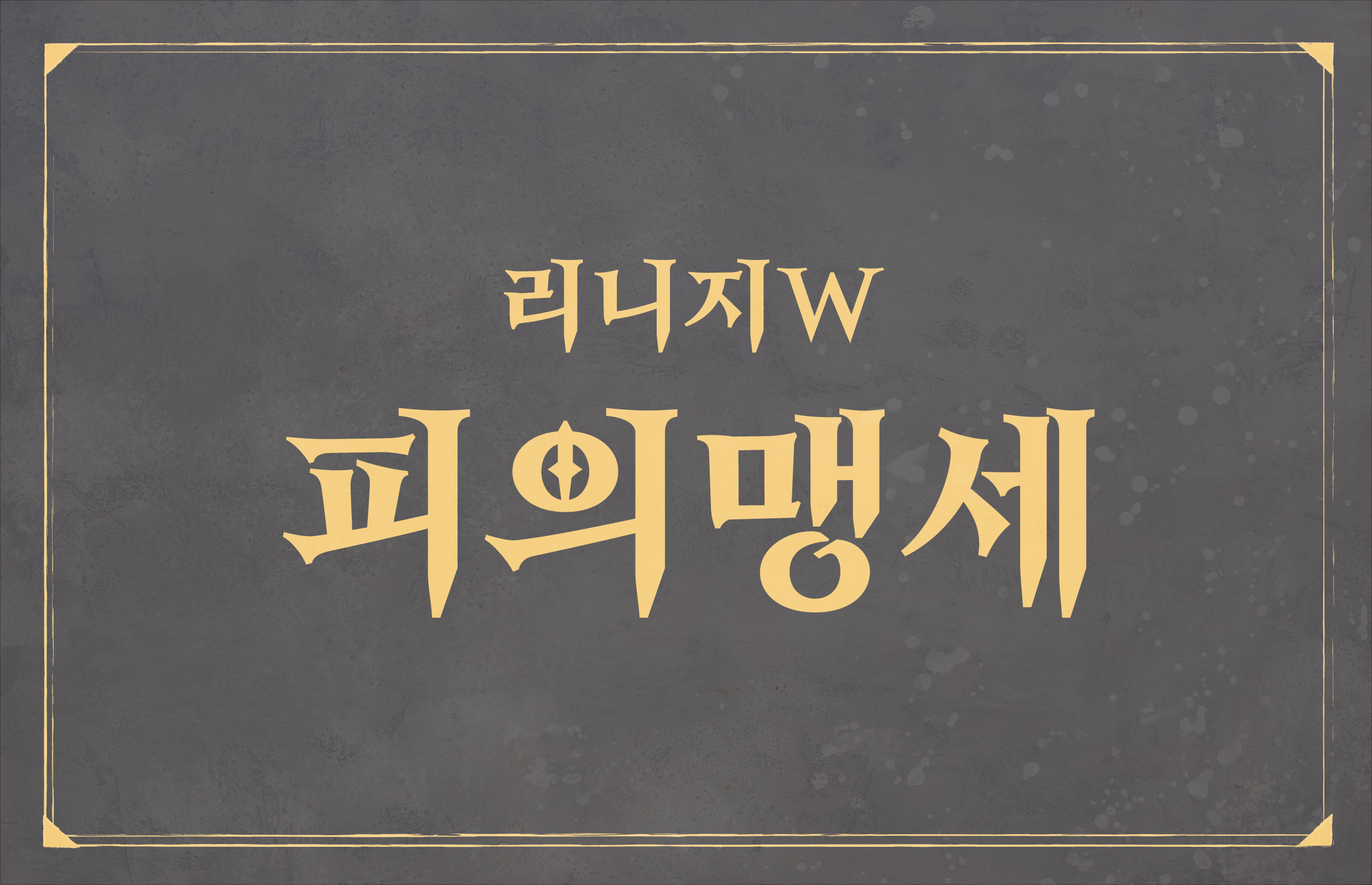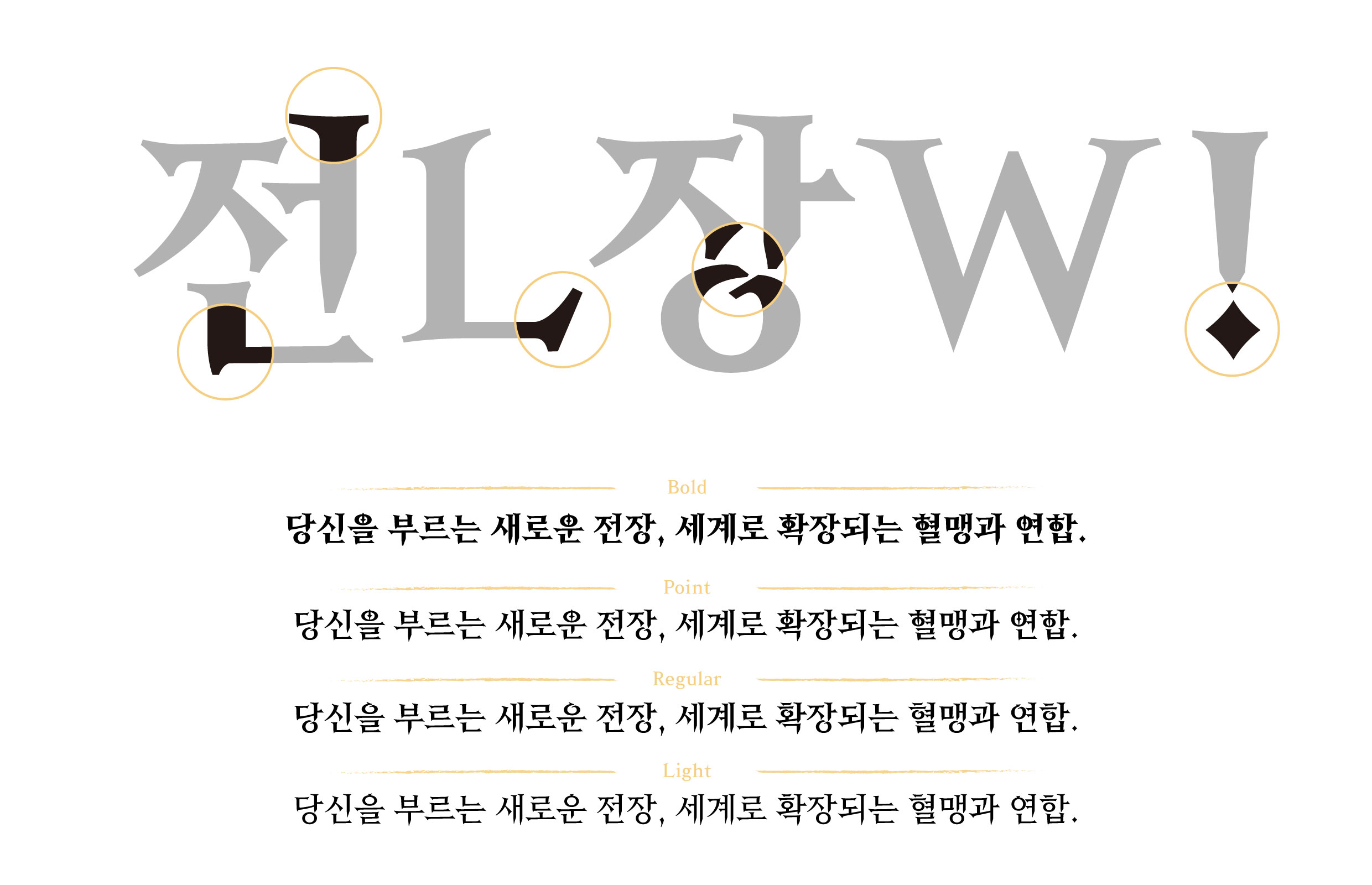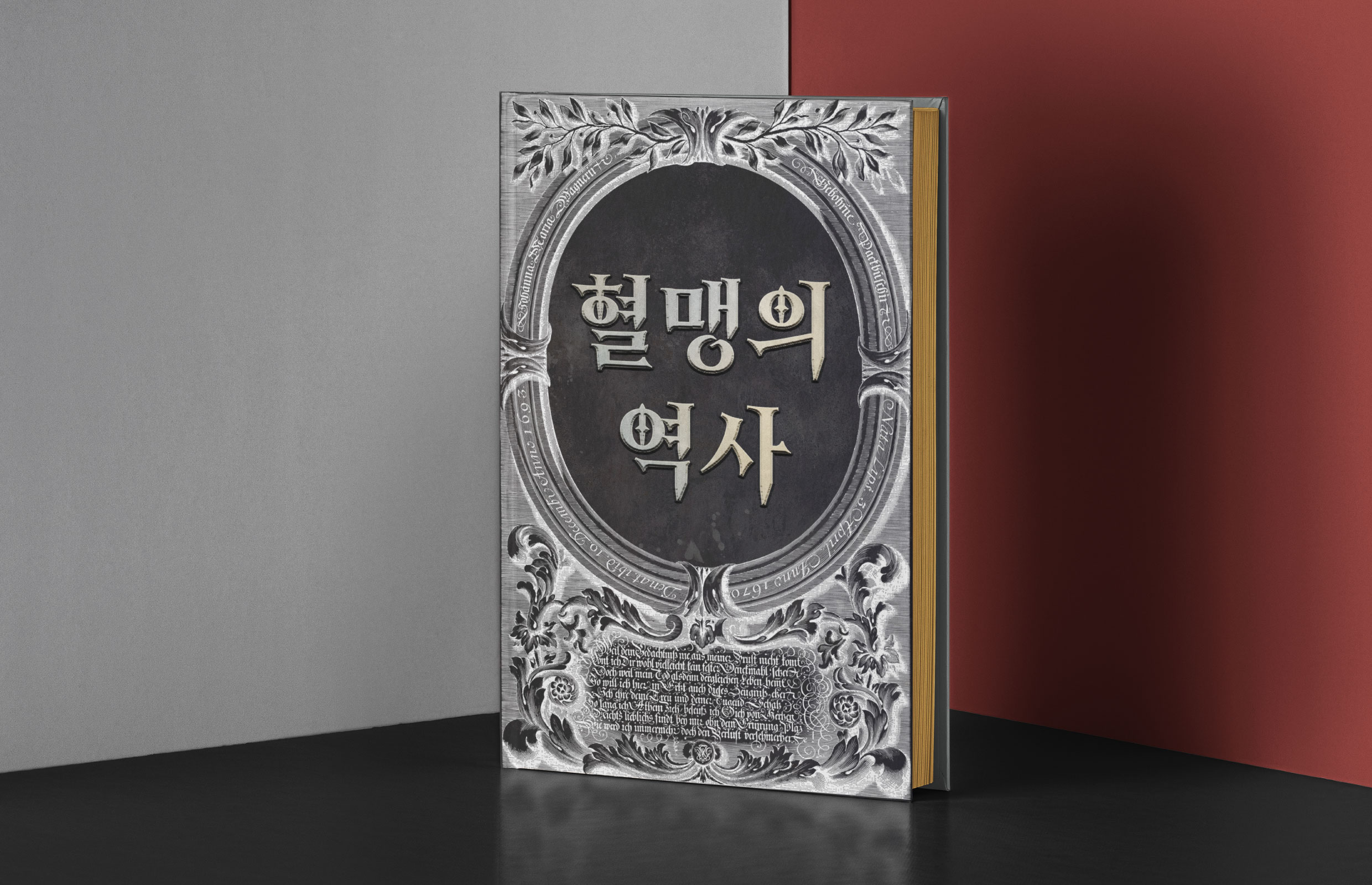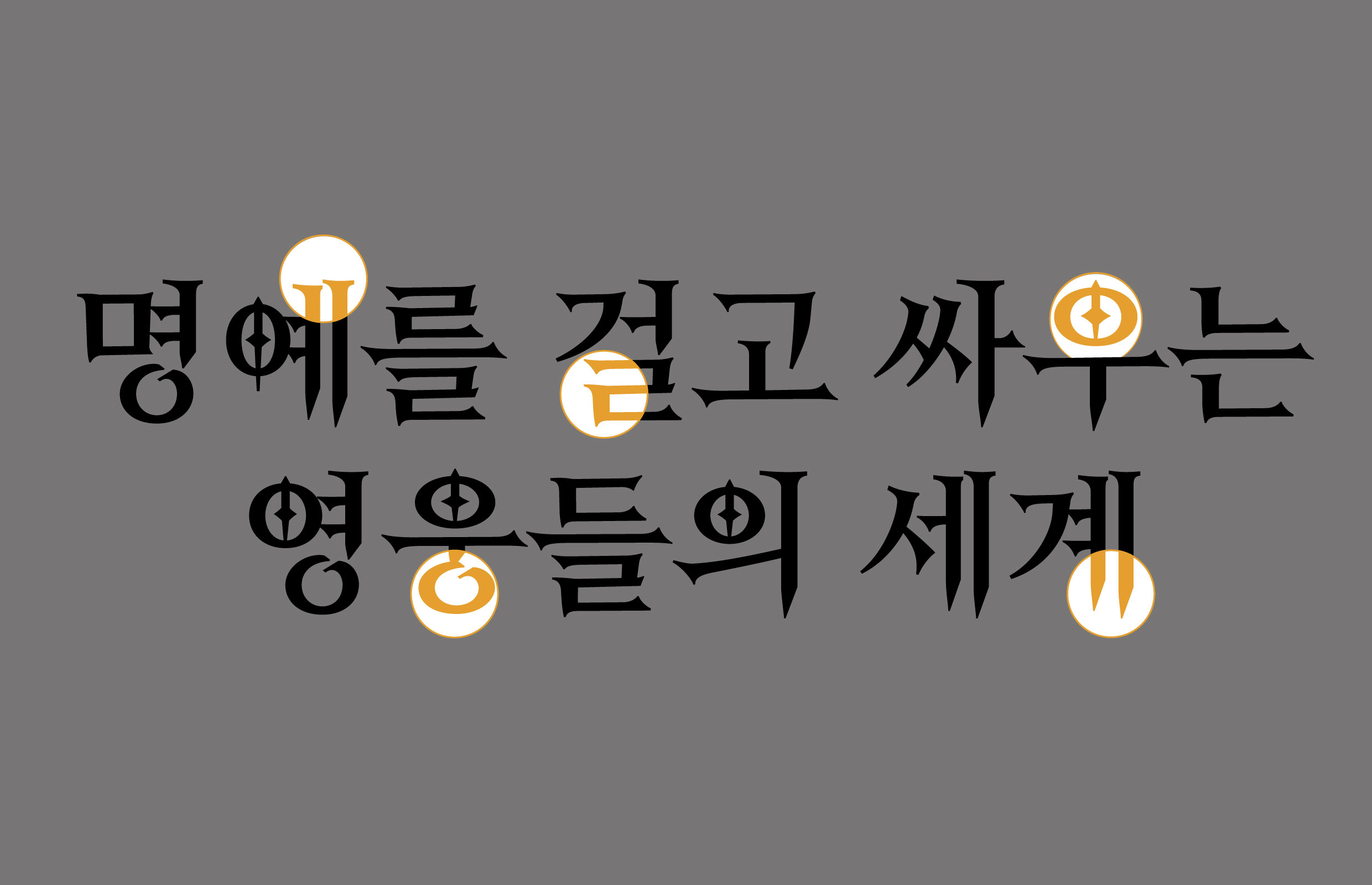
NCSOFT [리니지W]
게임 〈리니지W〉의 브랜드 아이덴티티를 강화하기 위해 제작한 서체. 판타지 세계가 배경인 게임 특유의 분위기를 글자에 녹여낸 점이 특징이다. 세리프 모양, 획 디테일 등 요소에 게임의 이미지를 반영하되, 게이머들의 가독성까지 고려하여 디자인했다.